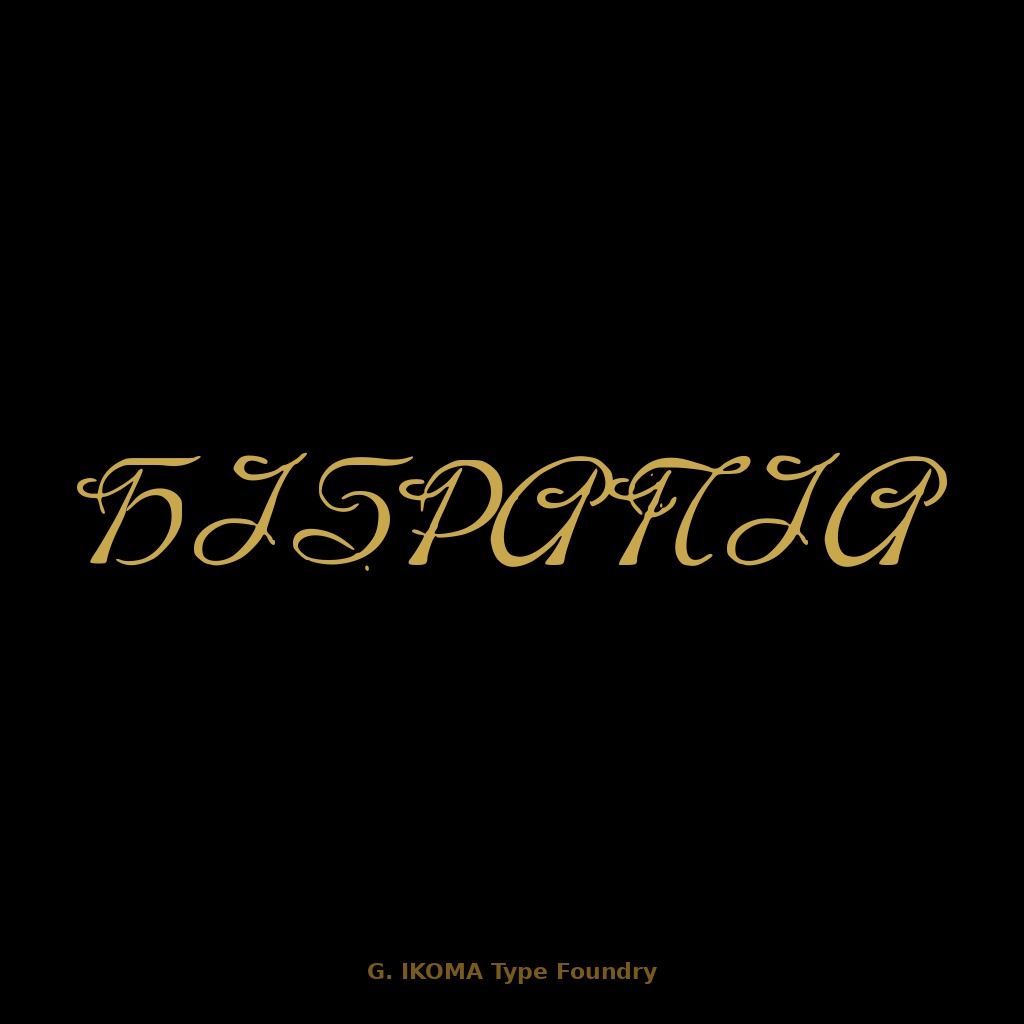
HISPANIA — 19世紀欧州印刷資料復元フォント / Historical Revival Typeface [Copperplate Script]
━━━━━━━━━━━━━━━━━━━━━━━━━ 【フォントについて】 ━━━━━━━━━━━━━━━━━━━━━━━━━ HISPANIA は、19世紀末〜20世紀初頭の欧州印刷資料を原典に、 手作業でトレース・デジタル化した復元フォントです。 ライプツィヒの名門活字鋳造所 J. G. Schelter & Giesecke の 正規製品として製造された銅版彫刻風筆記体(Copperplate Script) の復元です。原典資料にも「ORIGINALERZEUGNÍS DES HAUSES J. G. SCHELTER & GIESECKE, LEIPZIG」と明記されています。 細線・優雅な傾斜・装飾的なスワッシュ大文字が特徴です。 原典:Ludwig Petzendorfer, "Schriften-Atlas" または "Schriften-Atlas: Neue Folge" Julius Hoffmann, Stuttgart(パブリックドメイン) 様式:Copperplate Script / Engraving Script 収録グリフ:136文字(大文字・小文字・数字・記号・拡張ラテン文字) 欠落グリフ:なし 制作:株式会社生駒時計店 / G. IKOMA, LTD.(1870年創業) ━━━━━━━━━━━━━━━━━━━━━━━━━ 【収録内容】 ━━━━━━━━━━━━━━━━━━━━━━━━━ ・I_HISPANIA_Extended.ttf ・LICENSE.txt(日本語) ・thumb1〜4 サンプル・グリフチャート・原典カタログ・詳細文字見本 ━━━━━━━━━━━━━━━━━━━━━━━━━ 【推奨用途】 ━━━━━━━━━━━━━━━━━━━━━━━━━ ロゴ・ブランド名・招待状・名刺・パッケージ・ ウェディング関連デザインなど、 格調ある筆記体を必要とする用途に適しています。 本文組版・小サイズでの使用には向きません。 ━━━━━━━━━━━━━━━━━━━━━━━━━ 【ライセンス】 ━━━━━━━━━━━━━━━━━━━━━━━━━ 個人・商用利用ともに使用可能です。 再配布・転売・改変後の再配布は禁止です。 詳細はLICENSE.txtをご確認ください。 ━━━━━━━━━━━━━━━━━━━━━━━━━ 【原典資料について】 ━━━━━━━━━━━━━━━━━━━━━━━━━ 原典スキャンはG. IKOMA, LTD.が所蔵する実物資料から 独自にデジタル化したものです。 アーカイブサイト:https://g-ikoma-archive.netlify.app/ ━━━━━━━━━━━━━━━━━━━━━━━━━ BOOTH: https://g-ikoma.booth.pm/